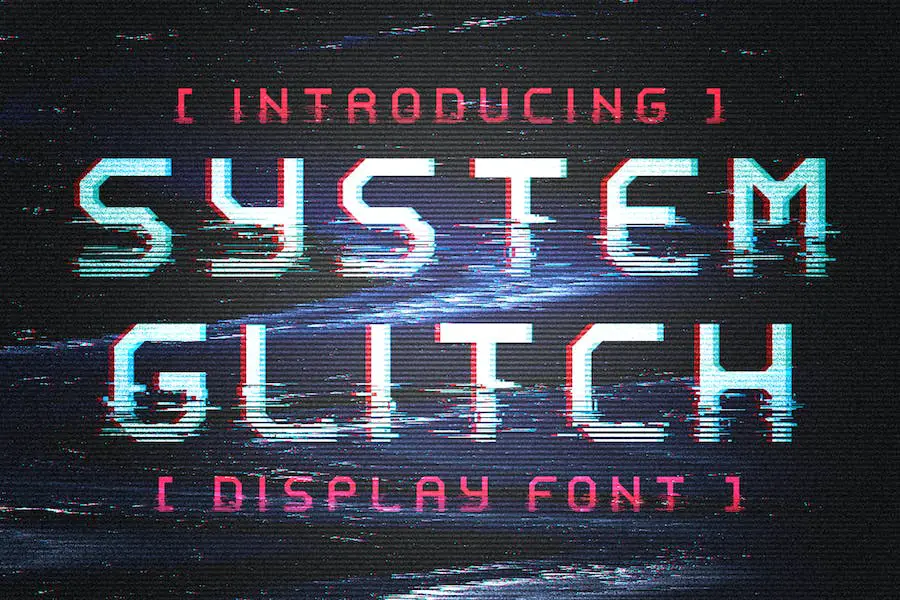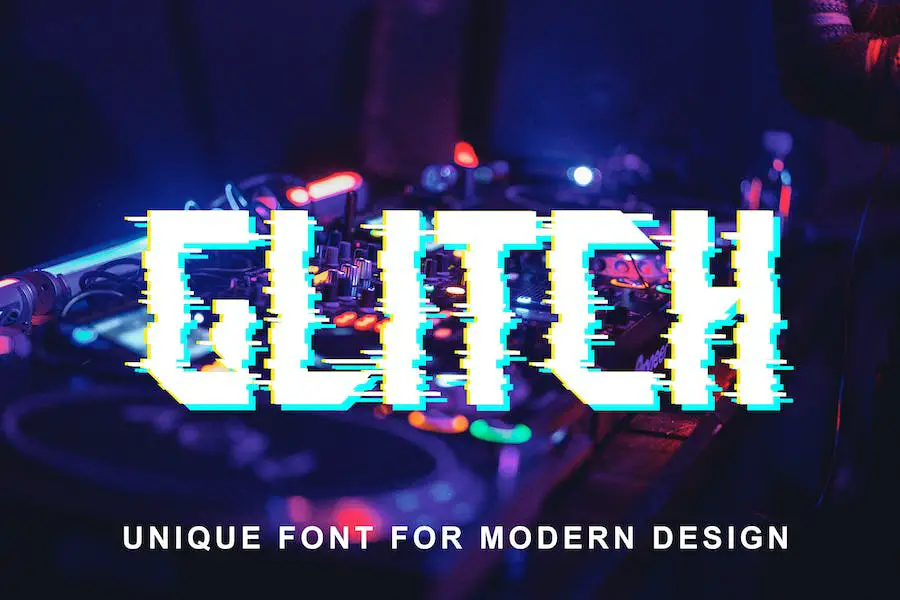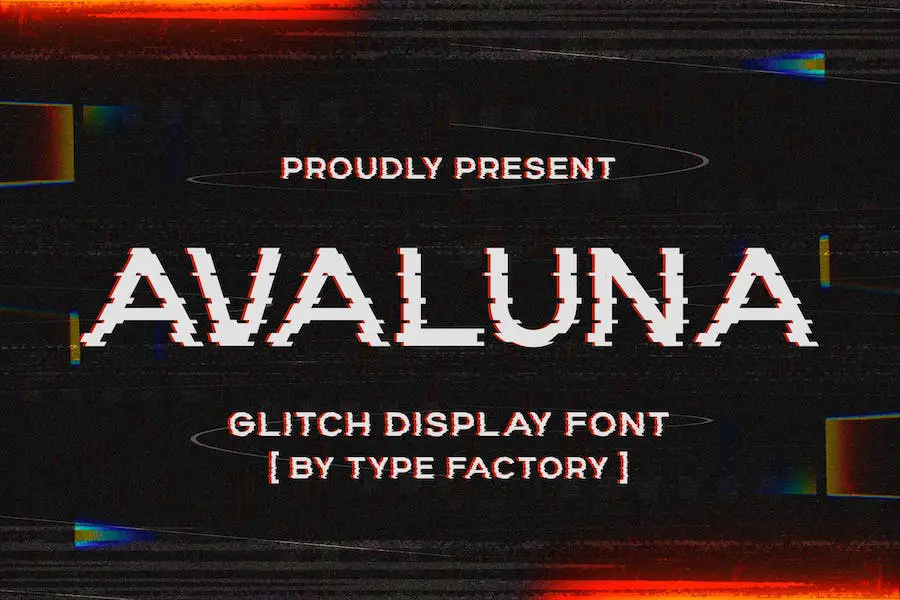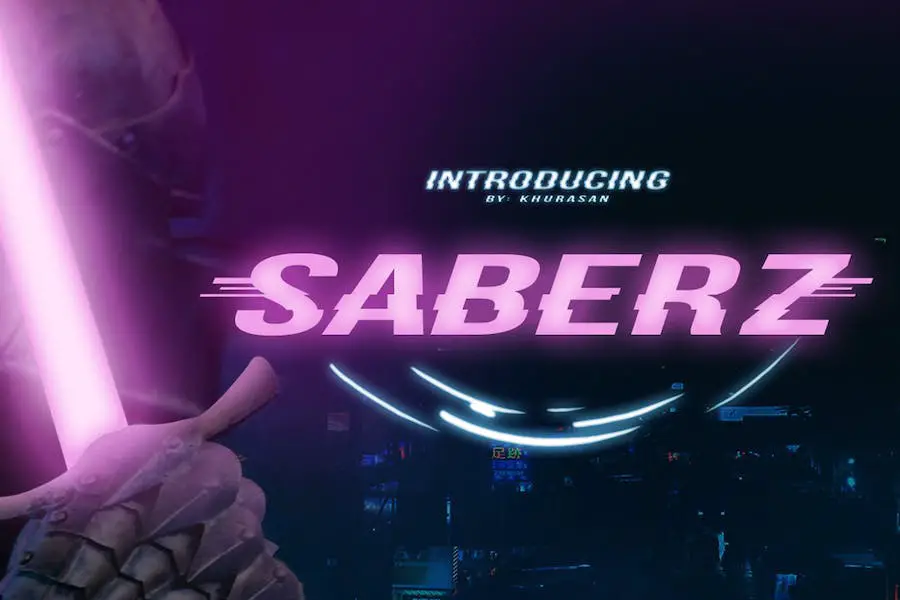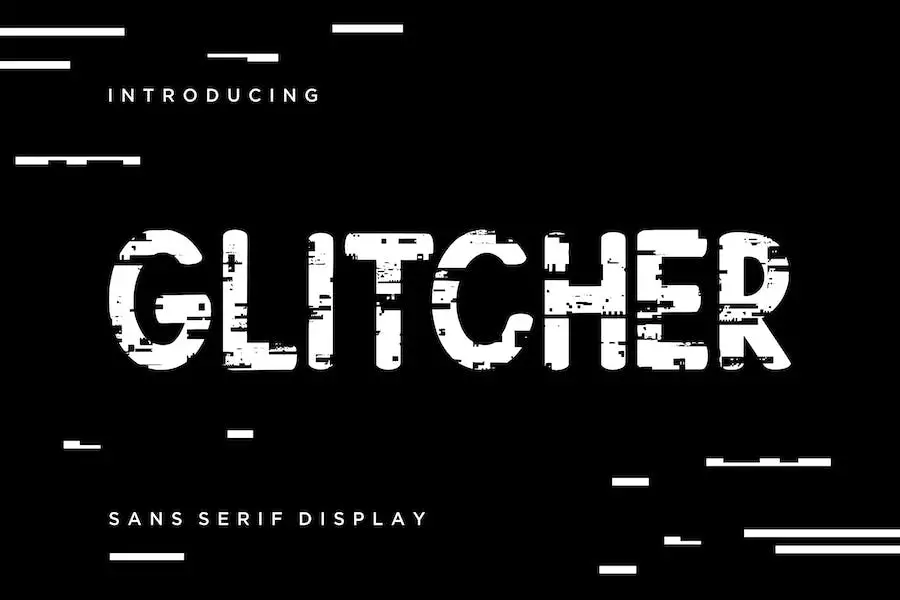
30 Font Glitch Terbaik 2023 (Gratis & Premium)
Diterbitkan: 2023-07-18Apakah Anda seorang desainer grafis yang sedang mencari font yang sempurna untuk meningkatkan proyek Anda? Tidak terlihat lagi dari posting blog ini di "30 Font Glitch Terbaik!"
Anda mungkin bertanya-tanya apa sebenarnya "glitch fonts" itu dan bagaimana mereka dapat meningkatkan desain Anda. Bersiaplah karena kita akan terjun ke dunia glitch font dan menemukan bagaimana mereka dapat menambahkan sentuhan unik dan edgy pada proyek desain grafis Anda.
Sekarang, mari kita mulai bisnis dan berbicara tentang apa sebenarnya font glitch ini. Font kesalahan adalah gaya tipografi yang meniru distorsi dan artefak digital yang sering terlihat pada teknologi yang tidak berfungsi.
Mereka menambahkan sentuhan kekacauan dan ketidakpastian pada desain Anda, membuatnya menonjol dari yang lain. Apakah Anda sedang mengerjakan iklan, situs web, logo, atau menggabungkan font glitch dapat langsung menambahkan getaran keren dan futuristik ke proyek Anda.
Pada artikel ini, kita akan menjelajahi 30 font glitch terbaik yang tersedia untuk Anda gunakan. Kami akan menampilkan fitur unik mereka dan memberi Anda informasi yang diperlukan untuk membuat keputusan berdasarkan informasi tentang font mana yang paling sesuai dengan kebutuhan Anda.
Setiap font akan disertai dengan deskripsi dan contoh penggunaannya untuk menyempurnakan desain Anda. Jadi, jika Anda siap membawa game desain grafis Anda ke level selanjutnya, teruslah membaca dan bersiaplah untuk terinspirasi oleh font glitch yang menakjubkan ini!
Font Kesalahan Premium Terbaik
Selamat datang di bagian font glitch premium terbaik! Jika Anda seorang desainer grafis yang ingin membawa proyek Anda ke level selanjutnya, Anda tidak akan mau melewatkan opsi font yang luar biasa ini.
Bersiaplah untuk menjelajahi pilihan font glitch pilihan yang akan menambahkan sentuhan unik dan menarik pada desain Anda. Pastikan untuk memeriksa produk-produk berikut dan temukan font glitch yang sempurna untuk proyek Anda berikutnya.
Avalon
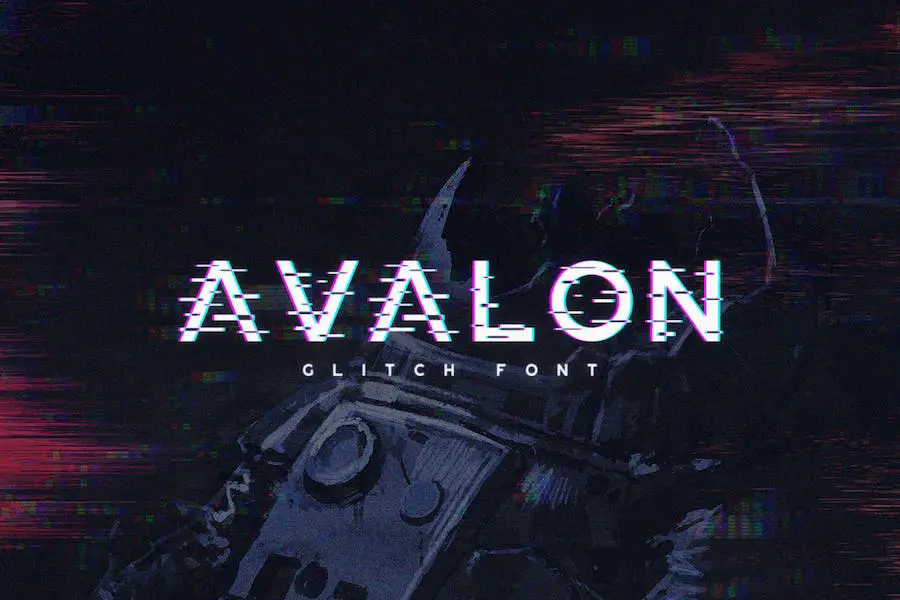
Avalon adalah font bertema kesalahan yang menawarkan serangkaian huruf besar, angka, dan tanda baca multibahasa. Ini sempurna untuk menambahkan efek distorsi digital pada desain Anda. Dengan gayanya yang unik dan edgy, Avalon menambahkan sentuhan kreativitas dan intrik pada proyek apa pun.
Apakah Anda sedang mengerjakan poster, logo, atau situs web, font ini pasti akan membuat pernyataan. Berikan desain Anda tampilan modern dan futuristik dengan estetika glitchy Avalon. Saatnya membawa grafik Anda ke level berikutnya dengan font dan efek glitch ini untuk distorsi digital.
Glitchy
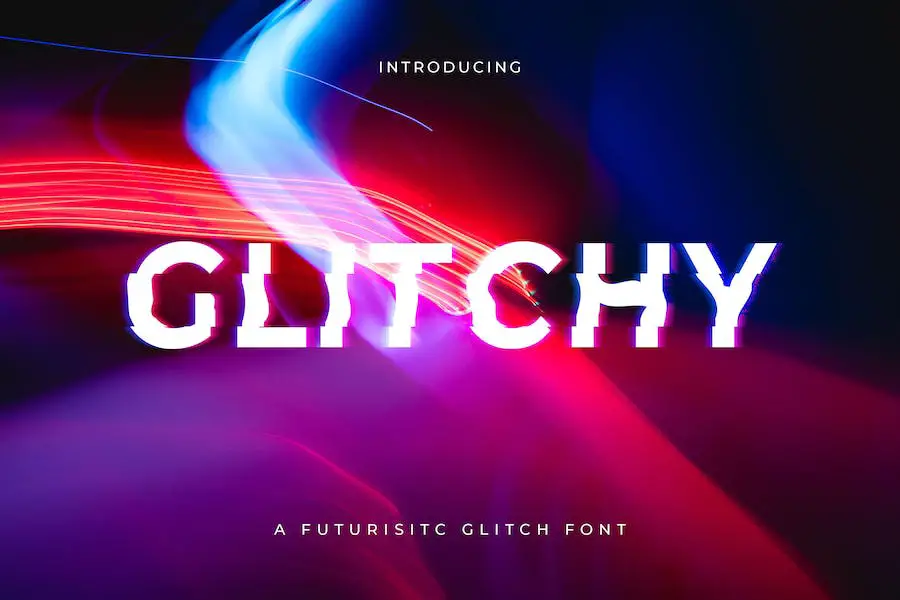
Glitchy adalah font unik dan serbaguna yang dapat menambahkan sentuhan distorsi digital dan sedikit cyberpunk pada desain Anda. Ini sempurna untuk membuat grafik futuristik dan edgy yang menonjol dari yang lain.
Salah satu fitur menonjol dari Glitchy adalah keserbagunaannya. Muncul dalam berbagai bobot dan gaya, memungkinkan Anda untuk bereksperimen dan bermain-main dengan efek yang berbeda.
Anda dapat memilih dari huruf tebal dan berdampak, atau memilih tampilan yang lebih halus dan glitchy. Kemungkinannya tidak terbatas dengan font ini.
Kesalahan Lucy
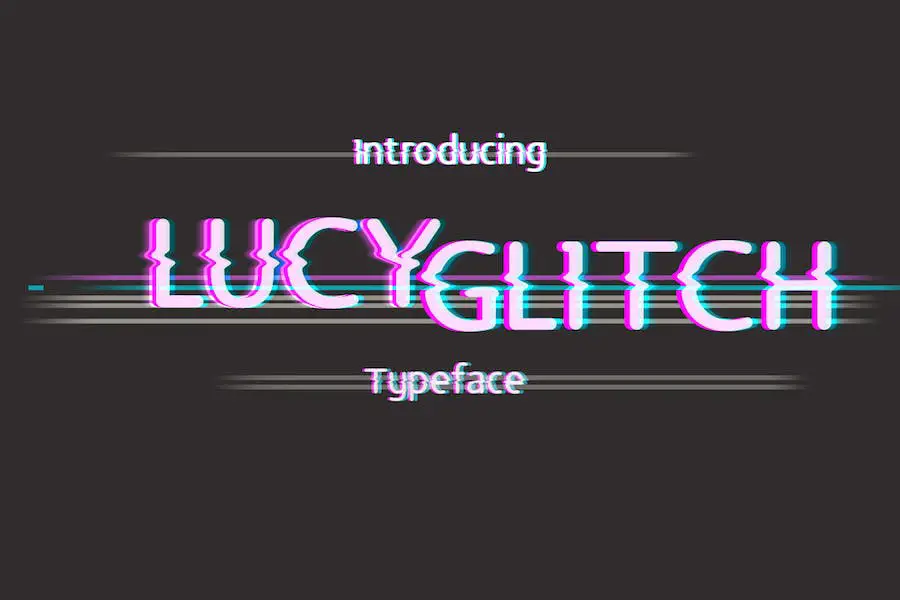
Lucy Glitch adalah tipografi unik yang menarik inspirasi dari kegagalan digital, mengubahnya menjadi desain yang menawan secara visual. Dengan kumpulan angka, ligatur sederhana, dan tanda baca, font ini sangat cocok untuk menambahkan sentuhan daya pikat pada kutipan dan judul Anda.
Baik Anda ingin membuat distorsi digital atau menggabungkan efek glitch modern, Lucy Glitch siap membantu Anda. Ini adalah pilihan yang sempurna untuk desainer grafis yang ingin meningkatkan proyek mereka dengan font yang mewujudkan keindahan ketidaksempurnaan dan inovasi.
Jadi mengapa tidak mencoba Lucy Glitch dan lihat bagaimana itu dapat mengubah desain Anda hari ini?
Singiko
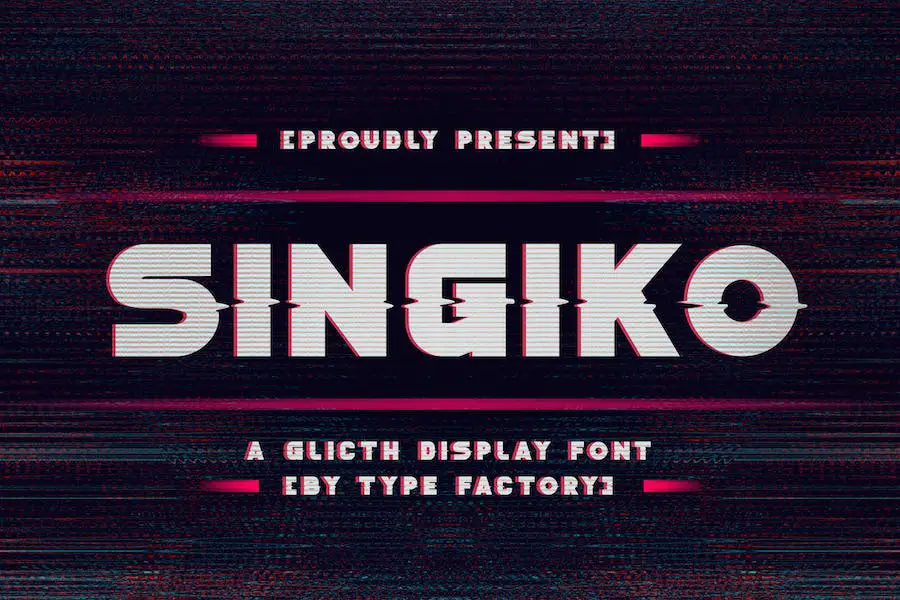
Singiko adalah jenis huruf yang unik dan bergaya yang menampilkan efek glitching digital artistik dan modern. Dengan akar yang dalam di masa lalu yang kelam, font ini telah menjadi representasi simbolis dari kekurangan dan kesalahan pada gambar digital melalui efek kesalahannya.
Rangkullah dunia glitch font yang inovatif dan memesona dengan Singiko. Dengan desainnya yang serba guna, ini menghadirkan sentuhan kecanggihan dan keunggulan pada proyek Anda, membantu Anda menonjol dari keramaian.
Jadi, jika Anda seorang desainer grafis yang ingin meningkatkan proyek Anda ke ketinggian baru, Singiko harus dimiliki dalam koleksi font Anda. Biarkan kreativitas Anda mengalir dan buat pernyataan berani dengan jenis huruf eksentrik yang menambahkan sentuhan kontemporer pada desain apa pun.
Debug